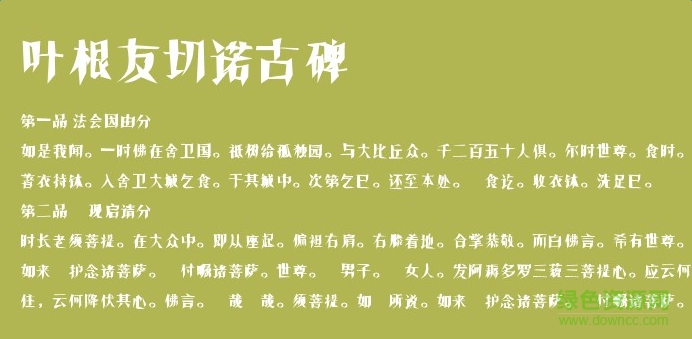
葉根友切諾古碑字體是一款粗獷彪悍風(fēng)格字體軟件,切諾古碑體字形比較粗大,非常震撼,適用于各大廣告海報標題的書寫,十分醒目,整體效果賞心悅目,還有更多好看字體歡迎來綠色資源網(wǎng)下載體驗!
葉根友切諾古碑字體是一款個性十足的字體,菱角分明,動感時尚,筆畫錯落有致,是標題字體和個性載體上非常貼切的選擇。